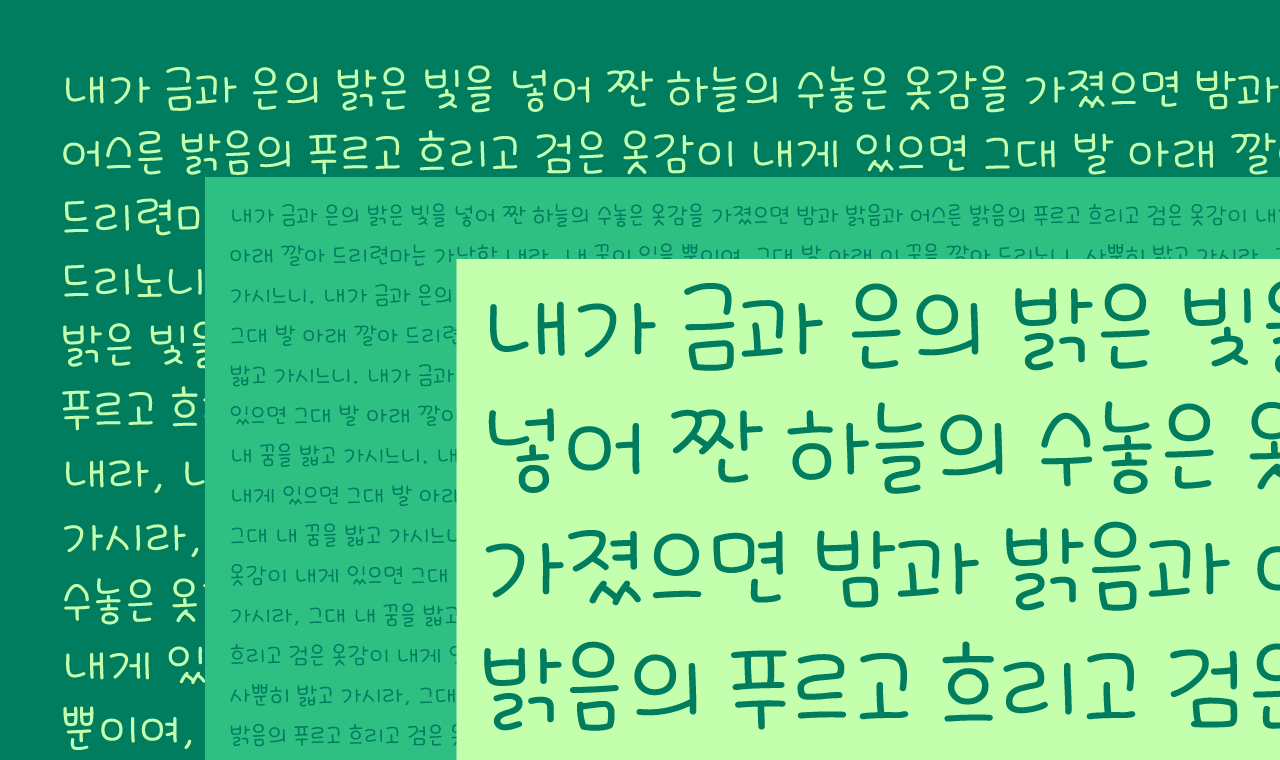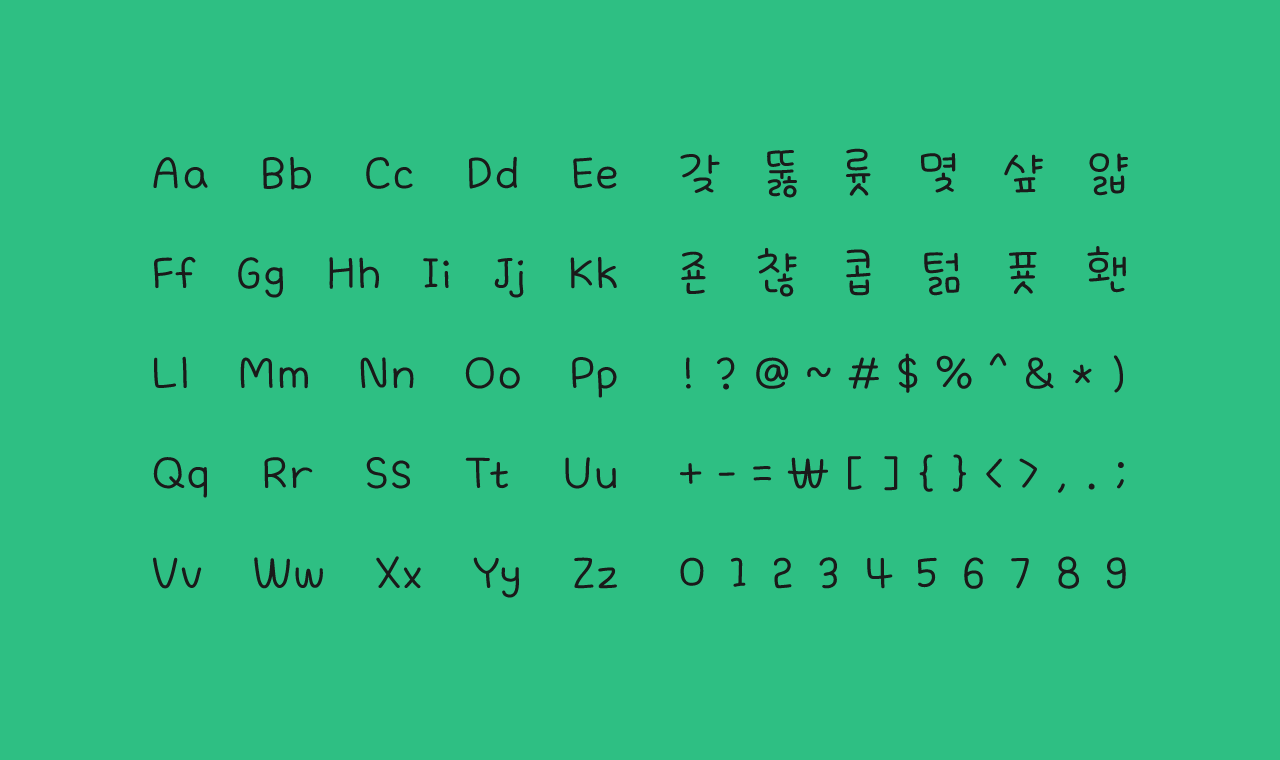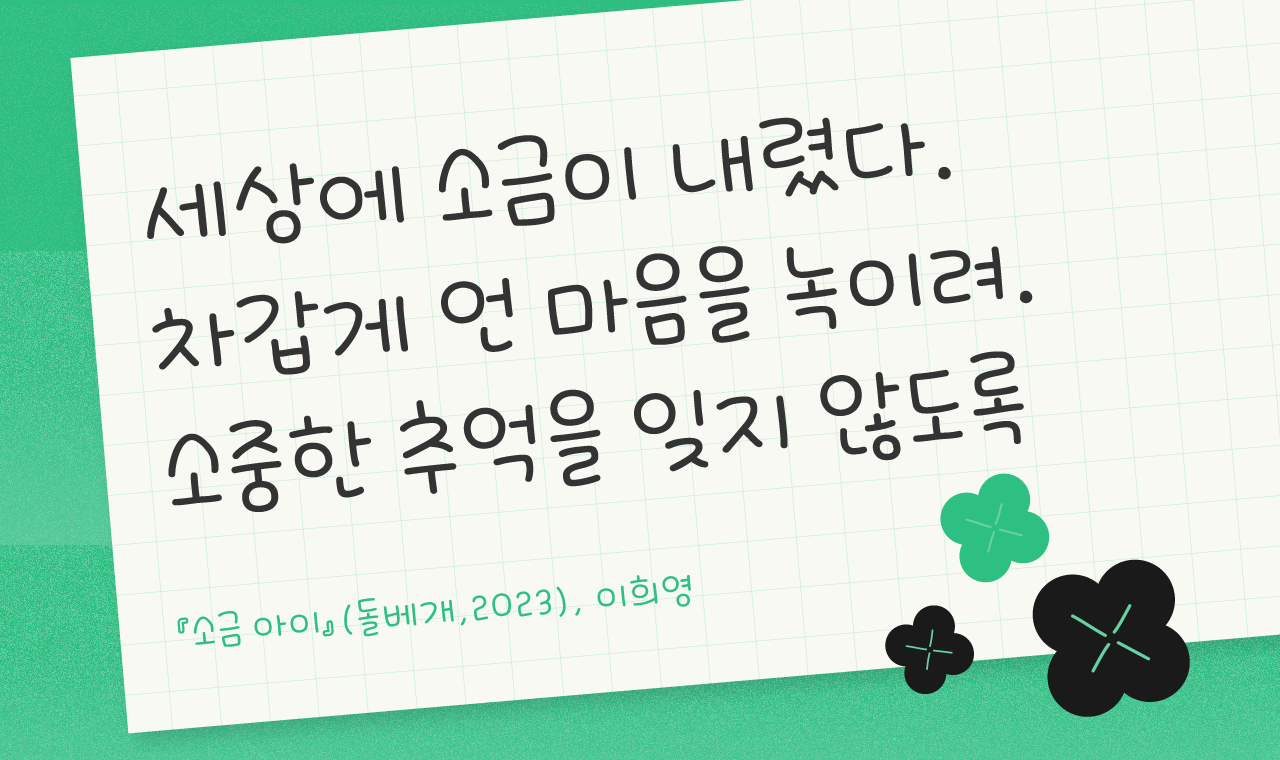
교보손글쓰기 [교보 손글씨 2024 박서우]
대산문화재단과 교보문고, 교보생명이 공동으로 매년 주최하는 ‘손글쓰기문화확산캠페인’을 통해 매년 하나씩 선정된 작품의 손글씨를 디지털 서체로 만들어 무료로 배포하는 프로젝트.
한글 11,172자 / 라틴 95자 / KS약물 986자